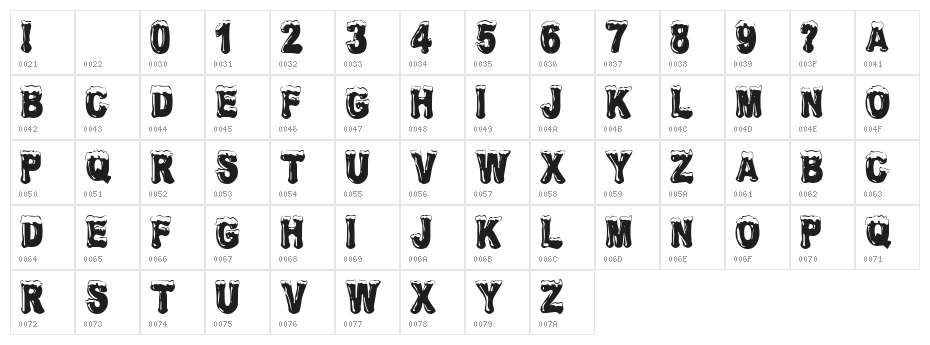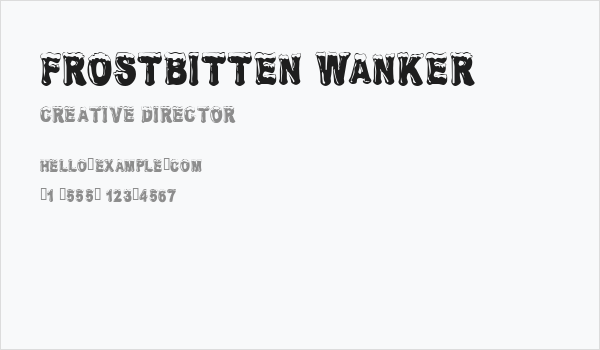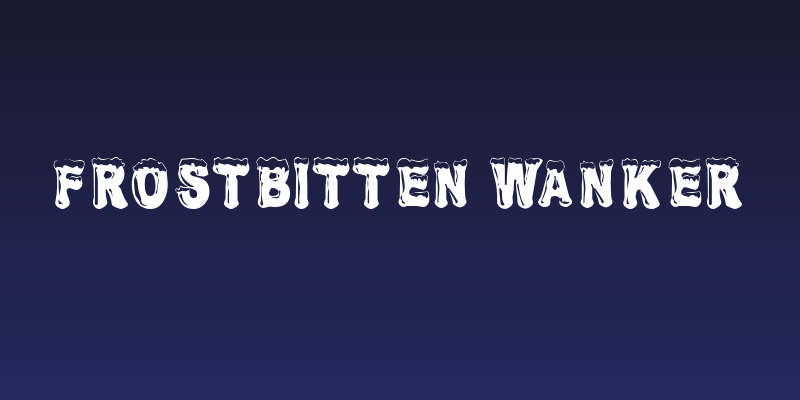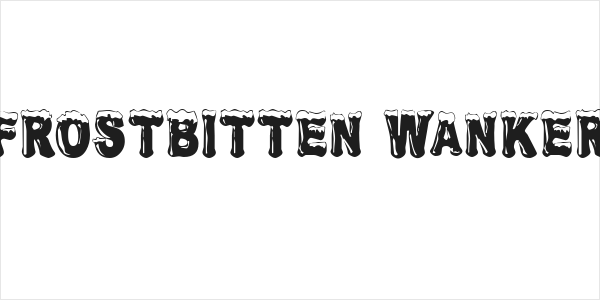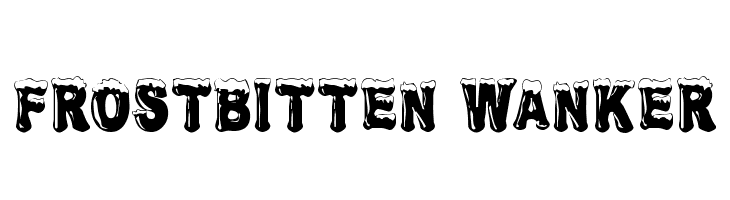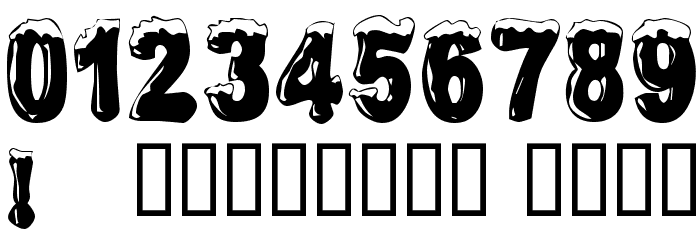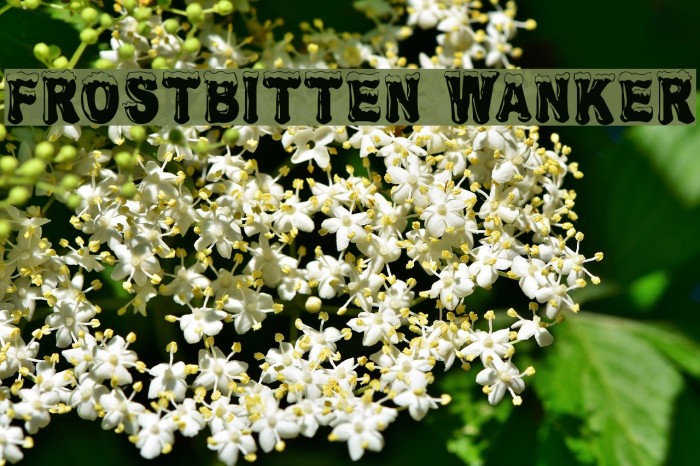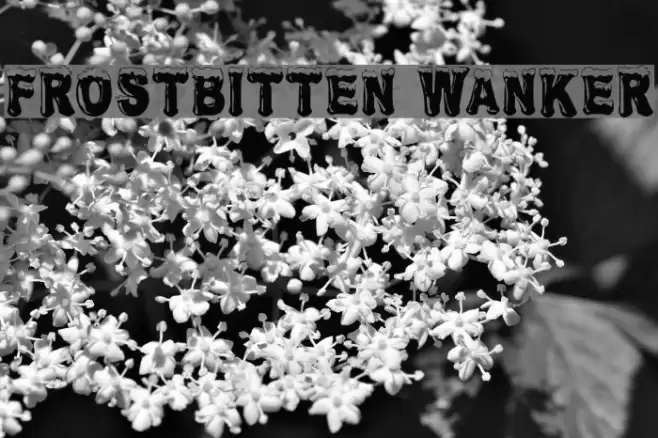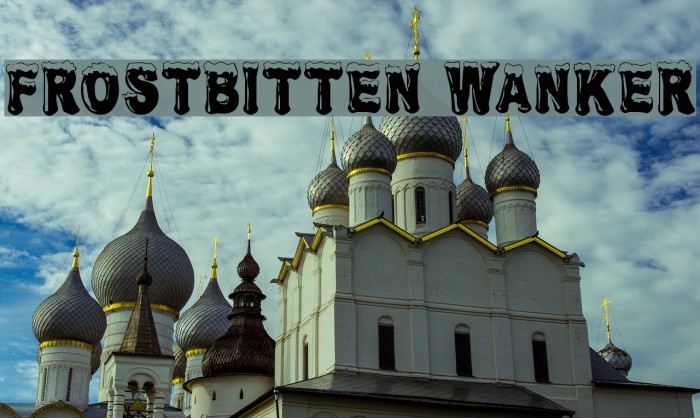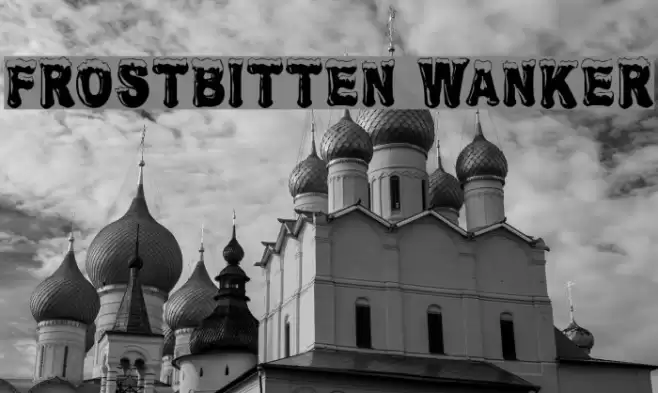
Frostbitten Wanker Font
| Projets proposés | Ideal for holiday cards, winter-themed posters, festive invitations, or any project needing a playful, seasonal touch. |